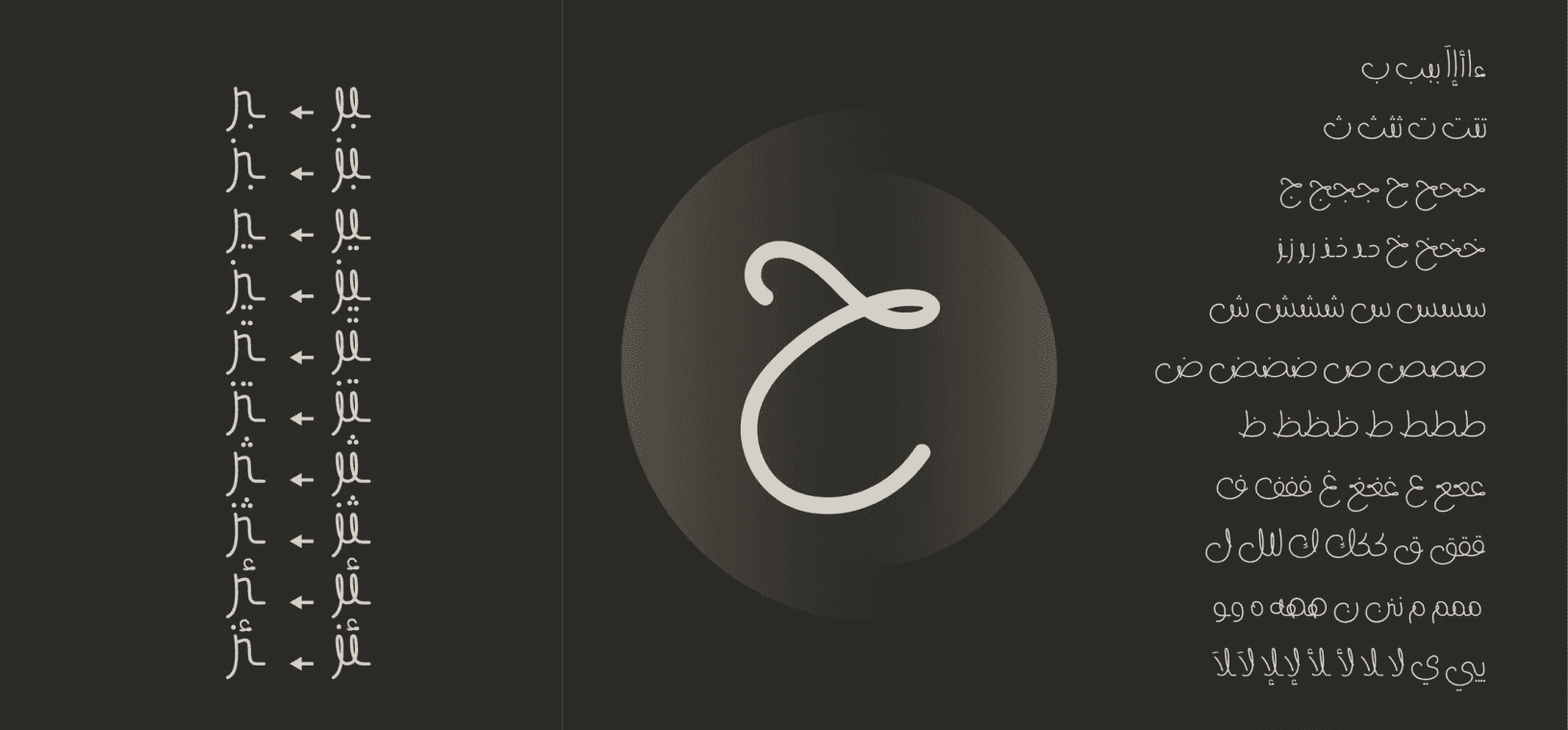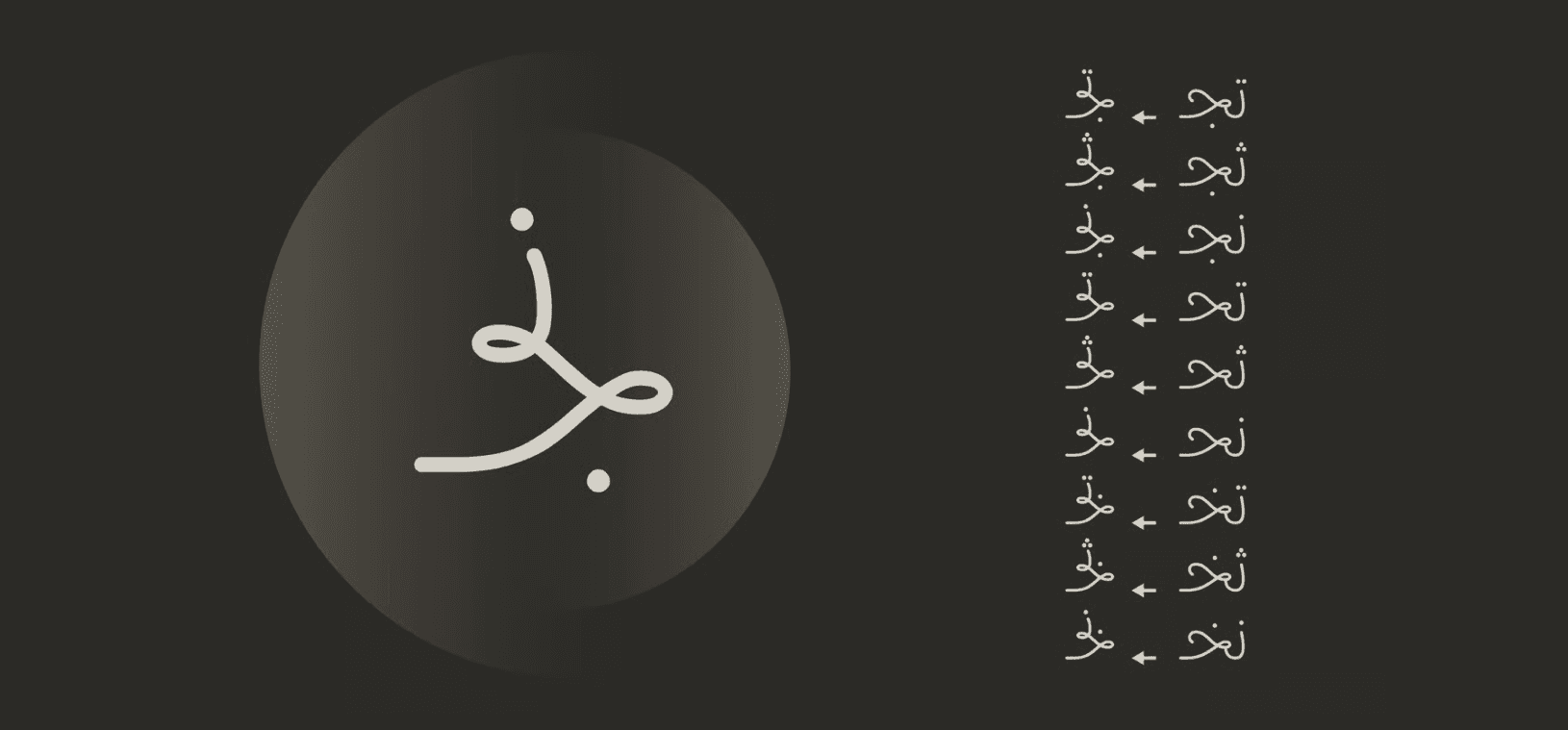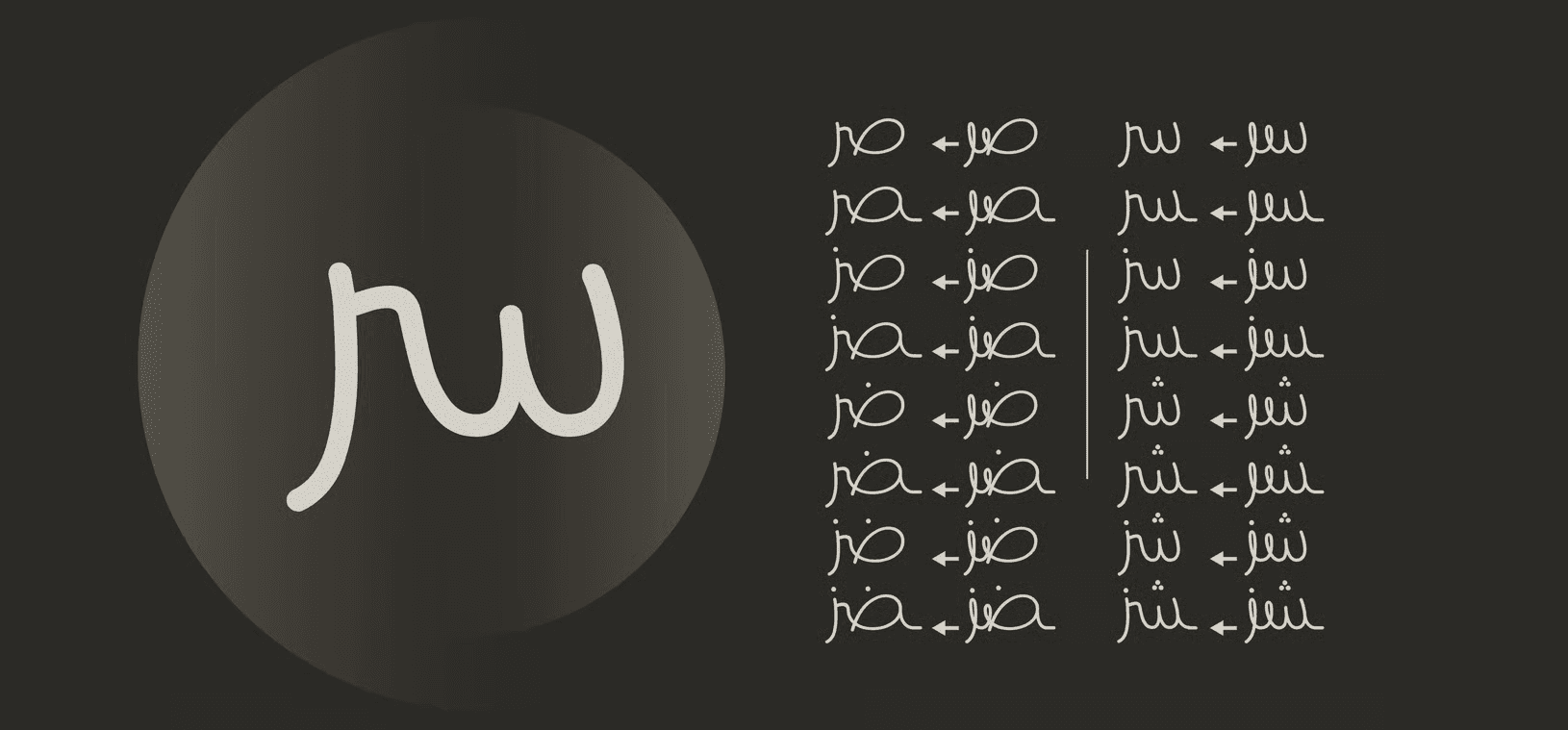
استلهم خط "زها" من روح المعمارية الراحلة زها حديد، ليمنح الحروف العربية لمسة أنثوية انسيابية، تجمع بين الحداثة والابتكار. يتميز الخط بتصميم فريد وعصري، يناسب مشاريع الهوية البصرية، والعناوين الجريئة، والتصميمات الإبداعية التي تتطلب طابعًا مميزًا ولافتًا. يتوفر الخط بتراخيص متعددة تناسب مختلف الاستخدامات من الأفراد إلى الشركات.